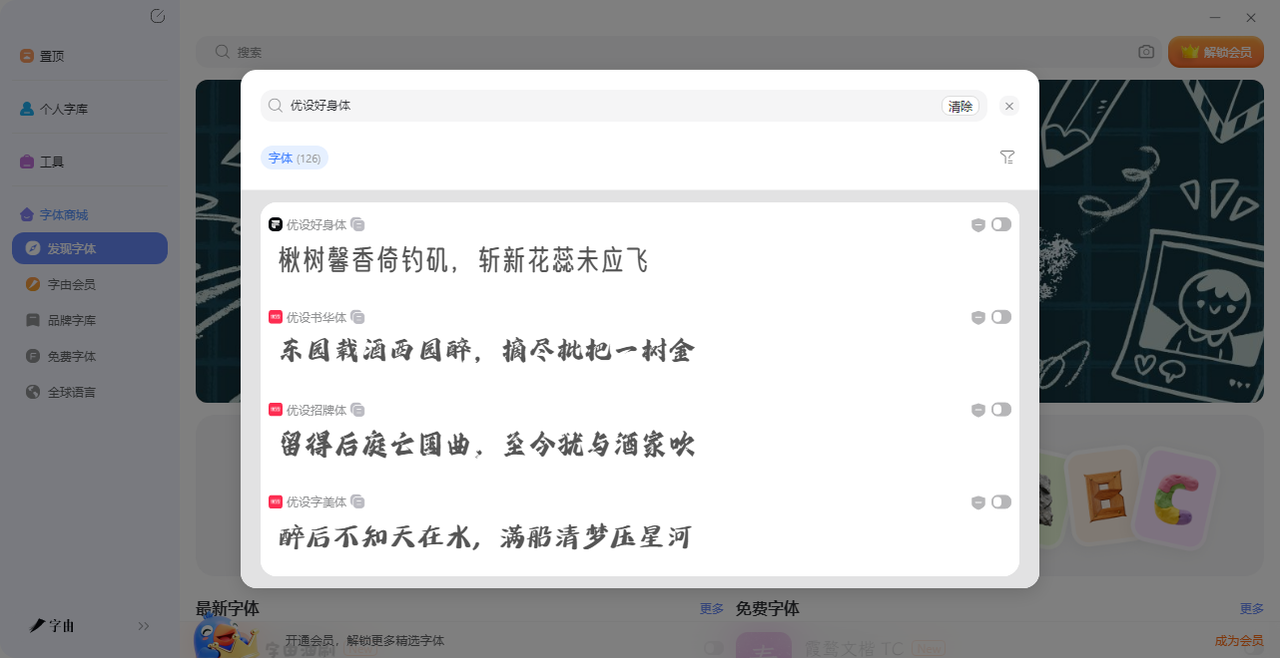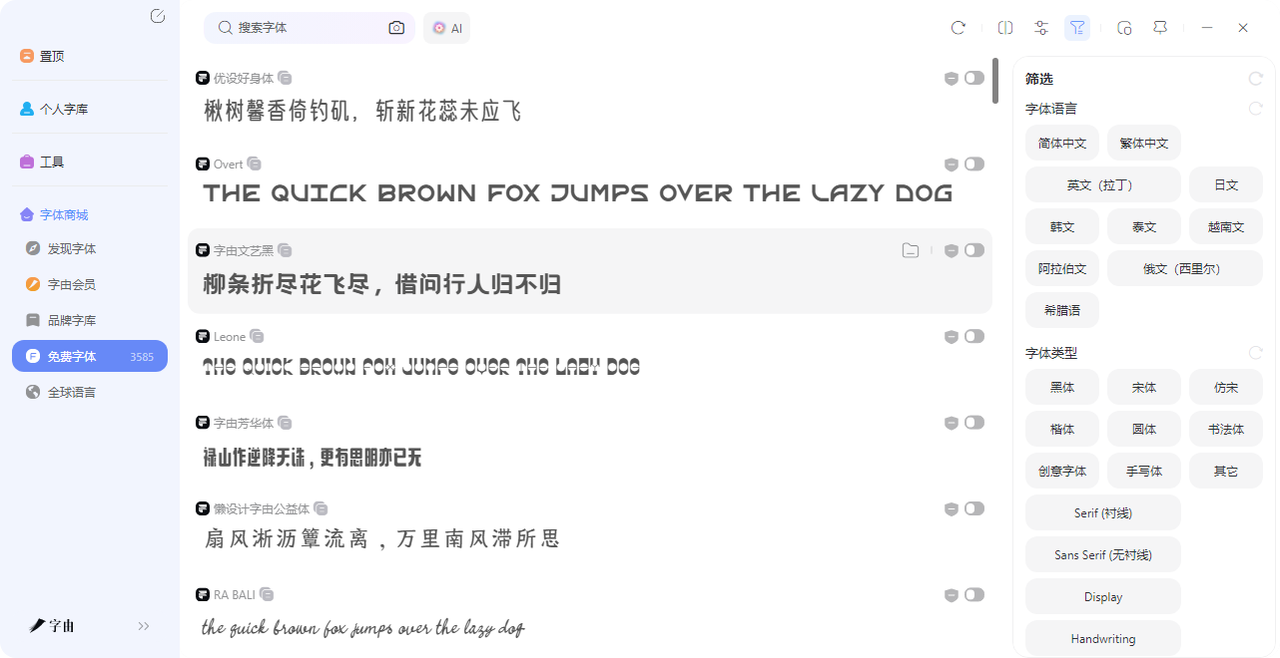
这几个字体网收藏好,做设计再也不怕缺字体
每次做设计,打开PS就开始翻字体库,翻来翻去就那么几款——黑体、宋体、楷体,顶多加个手写体。不是不想用别的,是真不知道去哪找。网上搜“免费字体”,出来一堆网站,点进去要么要注册,要么要付费,要么下载下来才发现不能商用。后来慢慢摸出门道:真正好用的字体网,其实就那么几个,一旦收藏好,就再也不用到处乱搜了。今天就把我私藏的5个字体网一次性整理出来,方便大家使用!需要的话记得收藏!
第一个要推荐的字体网是字由。它不只是一个下载站,更像一个“字体管家”——帮你把找字、筛字、用字、管字全包了。目前字由收录了超过10500款字体,其中3585 款是免费可商用的。
字由里目前有3585 款免费商用字体,涵盖了日常设计能用到的所有风格。我常用的几款有:
- 优设好身体:方正饱满,做画册内页、公众号配文很舒服
- 字由文艺黑:稳重但不死板,适合海报主标题
- 沐瑶软笔手写:圆润治愈,做亲子类、手账内容很对味
- 白路彤彤手写体:很有随意感的手写体,可以用在风景视频首页标题
- 点字浅夏体:清新手写,旅行vlog标题很出片
选字体的方式也很简单:有个筛选栏,点“免费商用”就只剩3585 款,再按风格选一下,基本就能锁定目标。看中哪款,点一下预览,输入自己的文字,效果好不好一眼就知道。
还有一个功能我很喜欢:个人云字库。以前换电脑,字体全没了,得重新下。现在把常用字体上传到云端,新电脑登录账号,直接就能用。不用U盘,不用网盘,省了不少事。
2、Adobe Fonts
Adobe Fonts 是Adobe Creative Cloud订阅用户的专属福利。如果你已经在用PS、AI、InDesign,那这个字体网就是你的隐藏宝藏。不需要额外付费,订阅CC就能免费使用上千款高质量字体。首页推荐了几款新字体:Indoor Kid Variable、Slight Chance Mono、Merwede、Brillante Variable……还有“当前趋势”板块,展示时下热门的字体。这些字体都是专业级设计,来源可靠,授权清晰。优势主要有:
- 和Adobe软件无缝集成,在PS、AI里直接就能用,不用下载安装
- 字体质量高,很多是独家合作款,别处找不到
- 支持可变字体,一个文件包含多个字重
门槛:需要订阅Creative Cloud,适合已经付费的设计师。如果你本来就是Adobe 用户,不利用这个资源就亏了。我特别喜欢它家的“当前趋势”板块,能看到最近大家都在用什么字体。而且它家的可变字体特别方便,一个文件就能调粗细,不用装好几个字重。而且它家的字体都是和Creative Cloud同步的,你在PS里激活的字体,AI里也能直接用,不用重复操作。做跨软件设计的时候特别方便。
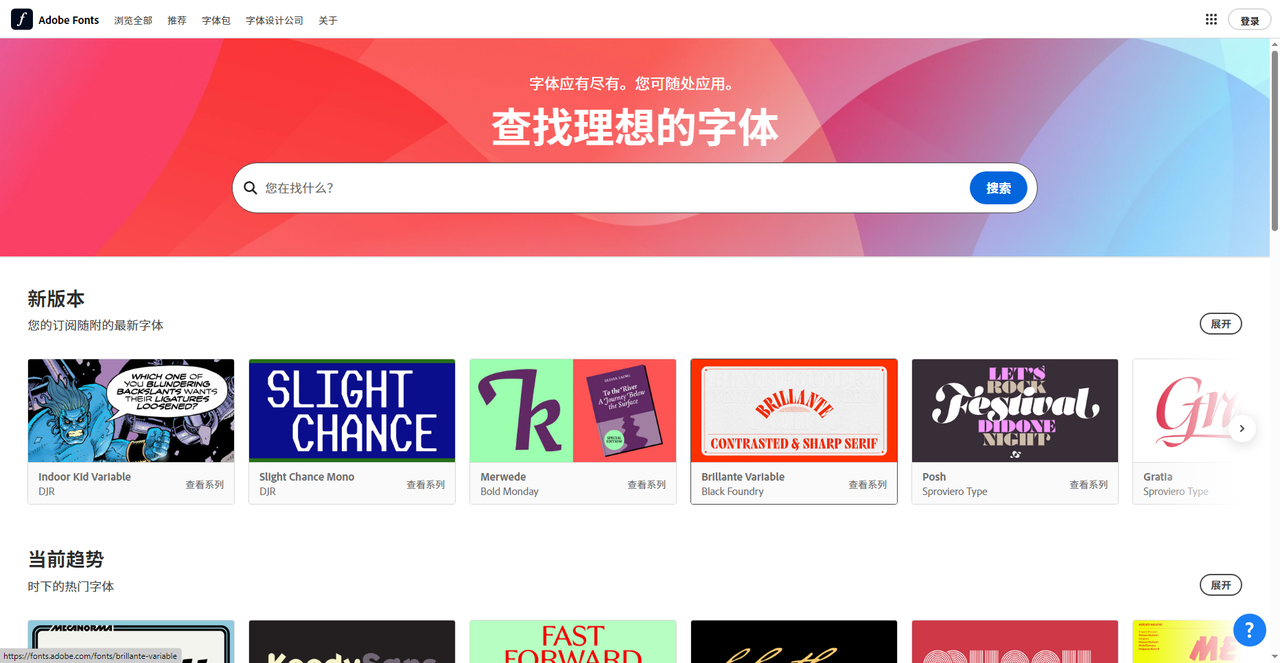
3、Alkes
Alkes 是一个精品字体销售平台,首页显示“50% OFF”——在打折。和前面几个免费网站不同,这里的字体需要付费购买,但质量非常高,适合对字体有苛刻要求的项目。从主页看,它推荐了多款热门字体:
- Panton Arabic:10种字重,$23起,支持阿拉伯文
- POSTAMP GROTESK:11种字重,$25起,现代无衬线体
- Trixy:15种字重,$24起,风格多变
它还提供了“Font Tester”功能,可以在购买前输入自己的文字实时预览效果,避免买到手才发现不合适。如果你做品牌设计、高端包装、或者需要独家字体,这里值得逛逛。我特别喜欢它家的“Font Tester”功能,买之前先输入自己的文字看看效果,不用担心买回来不合适。而且它家经常打折,可以蹲一下。
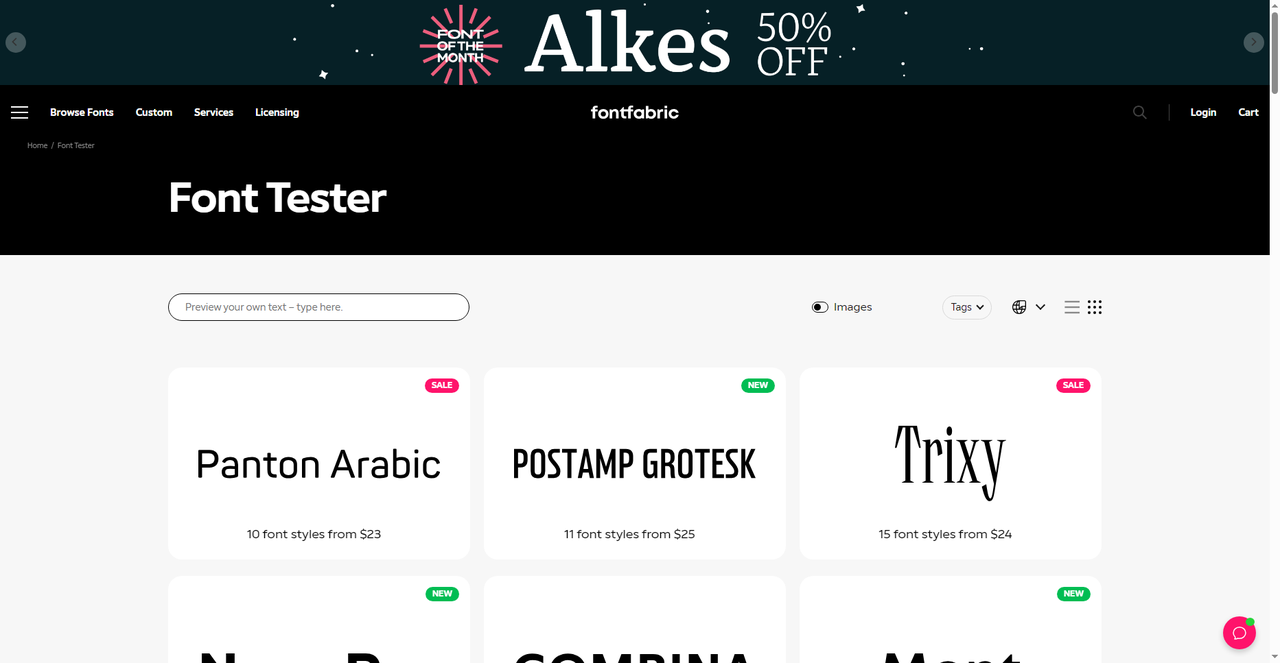
4、Fontsource
Fontsource 是一个开源字体平台,目前收录了2071个字体家族。它的定位和其他字体网不太一样——主要面向网页开发者,提供自托管的开源字体。而且它还展示了几款热门开源字体:Inter(可变字体)、Roboto、Open Sans、Poppins、Montserrat……这些都是Google Fonts上的经典款。每个字体都可以直接下载,或者通过npm安装,用于网页开发。并且你可以发现这个网站:
- 全部开源,免费商用
- 支持可变字体,一个文件搞定所有字重
- 自托管,不用担心CDN被墙或加载慢
如果你做网页开发,或者需要一款稳定、开源的字体库,Fontsource很对口。它不需要注册,不用付费,打开就能用。我特别喜欢它家的“可变字体”,一个文件就能调出各种粗细,做网页的时候特别方便。而且它家的字体都是开源的,用起来完全不用担心版权。另外它家的npm安装方式也很方便,做网页项目的时候,直接命令行装一下就能用,不用手动下载字体文件。而且它家的文档写得很清楚,新手也能看懂。
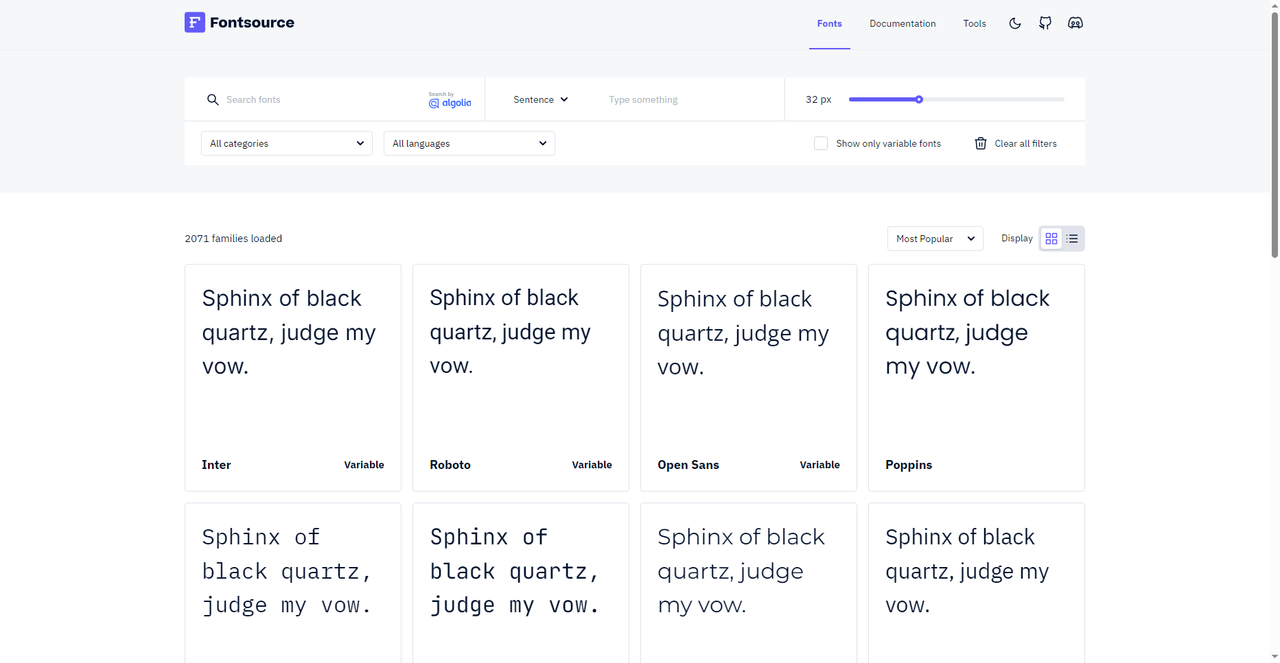
5、Cufon Fonts
Cufon Fonts 是一个运营多年的老牌字体网,分类清晰,首页顶部有Serif、Sans-Serif、Display、Handwritten、Monospaced、Symbol等常用分类。它的特色是“专题合集”功能。从分类来看它整理了各种主题的字体合集:
- Cinematic Fonts:电影感字体,适合海报、预告片
- Magazine Fonts:杂志风格字体,适合排版
- Study Fonts:学习笔记字体,清晰易读
- Youtuber Fonts:适合视频创作者的字体
- Tatto Fonts:纹身风格
- Y2K Fonts:千禧年复古风
- Science Fonts:科技感字体
- Girlblogger Fonts:适合女生博客的字体
每个合集都有几十到上百款字体,点进去就能浏览。截图底部还显示“Recommended by Cufon Fonts”,有人气推荐字体可供参考。下载前记得看一下授权说明,有的是免费个人使用,有的是免费商用。我特别喜欢它家的“专题合集”,做电影海报直接点Cinematic Fonts,出来的都是电影感强的字体。而且它家的“Recommended”板块也很实用,都是编辑精选的,质量有保障。而且它家的“按字母排序”也很实用,知道字体名字的话直接按字母跳转,不用一页页翻。
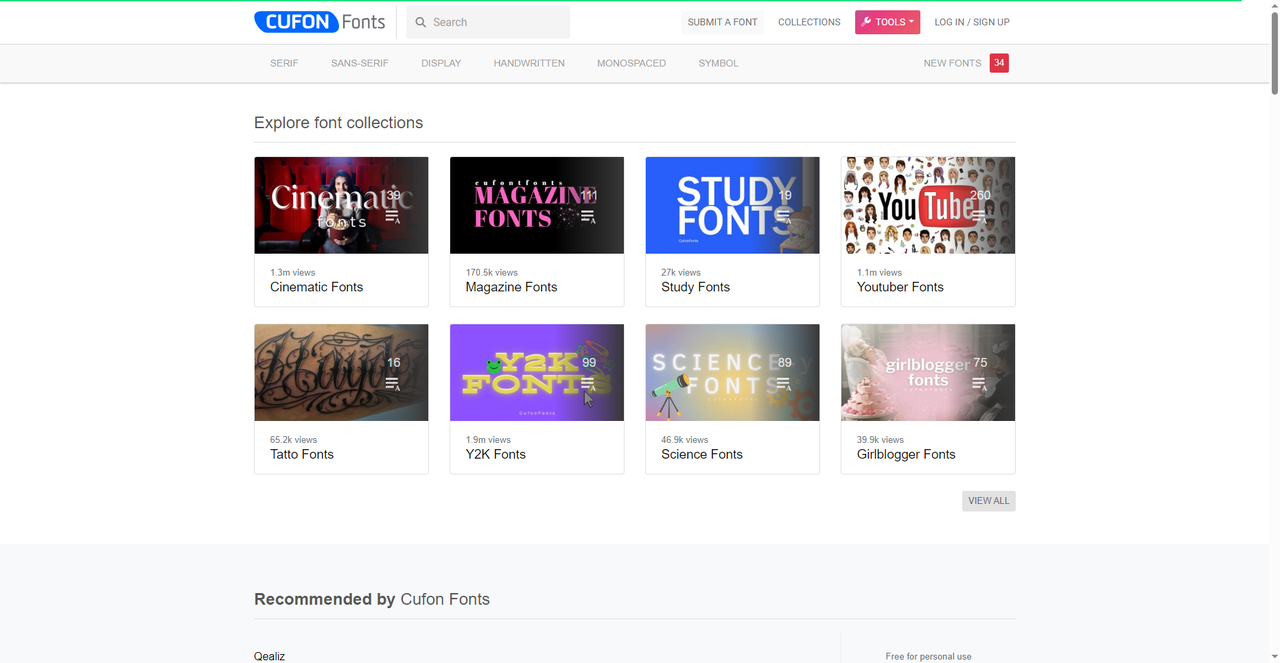
这5 个网站是我精挑细选整理好的内容,不论是那一款你都可以在里面找到海量高质的字体,有免费的也有付费的,这个可以看个人需求。但是如果问我最近最常用的是哪一个,我的回答是字由。字由对我来说它不只是一个下载站,更是一个帮你管好字体的“管家”。如果你也在为找字体发愁,不妨从字由开始试试,让设计再也不怕缺字体。